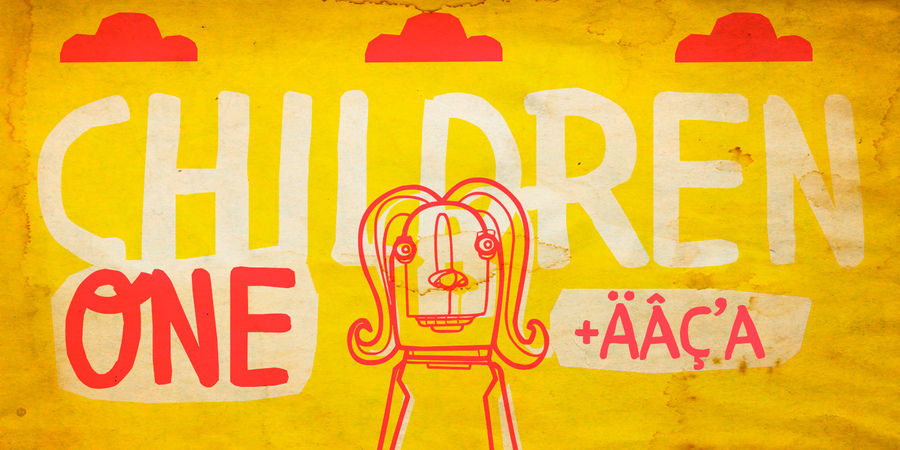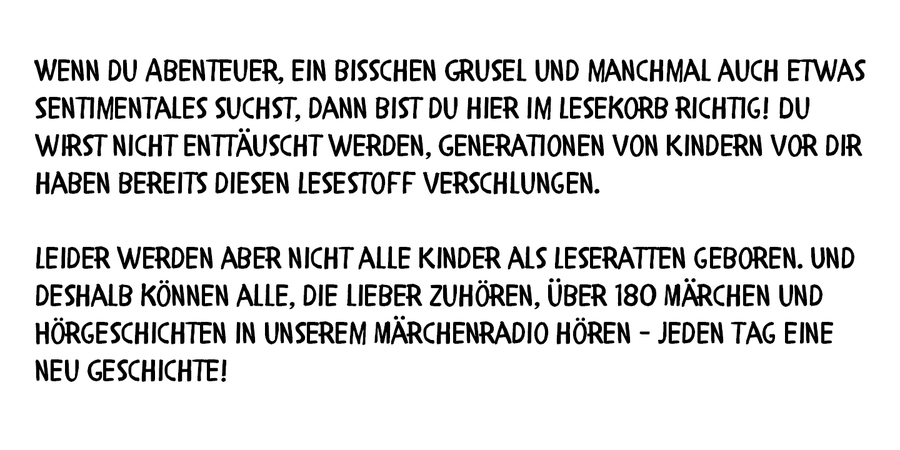
Шрифтова пара з CoolKids Light (1 з 9)Опис шрифта Children One – неформальний рукописний шрифт із доброзичливим грайливим настроєм з підтримкою безлічі європейських мов, а також кирилиці та грецької. Цей шрифт має потужні можливості у вигляді альтернативних гліфів, розчерків та рідкісних лігатур. Шрифт Children One розробив Родріго Арая Салас у 2014 році.
Асоціації з сімейством шрифтів Children OneОсобистість і характер гарнітури:
добрий, добродушний, вуличний, доброзичливий, побутовий, крафтовий, неформальний, мультяшний, ручний, наївний, рукотворний, кустарний, саморобний, високий, оригінальний, живий, характерний, грайливий, помітний, домашній, виразний, неохайний, рухливий, непосидючий, ремісничий, потішний, милий, цікавий, творчий, симпатичний, артізанальний, природний, натуральний, недбалий, вернакулярний, зимовий, сніжний